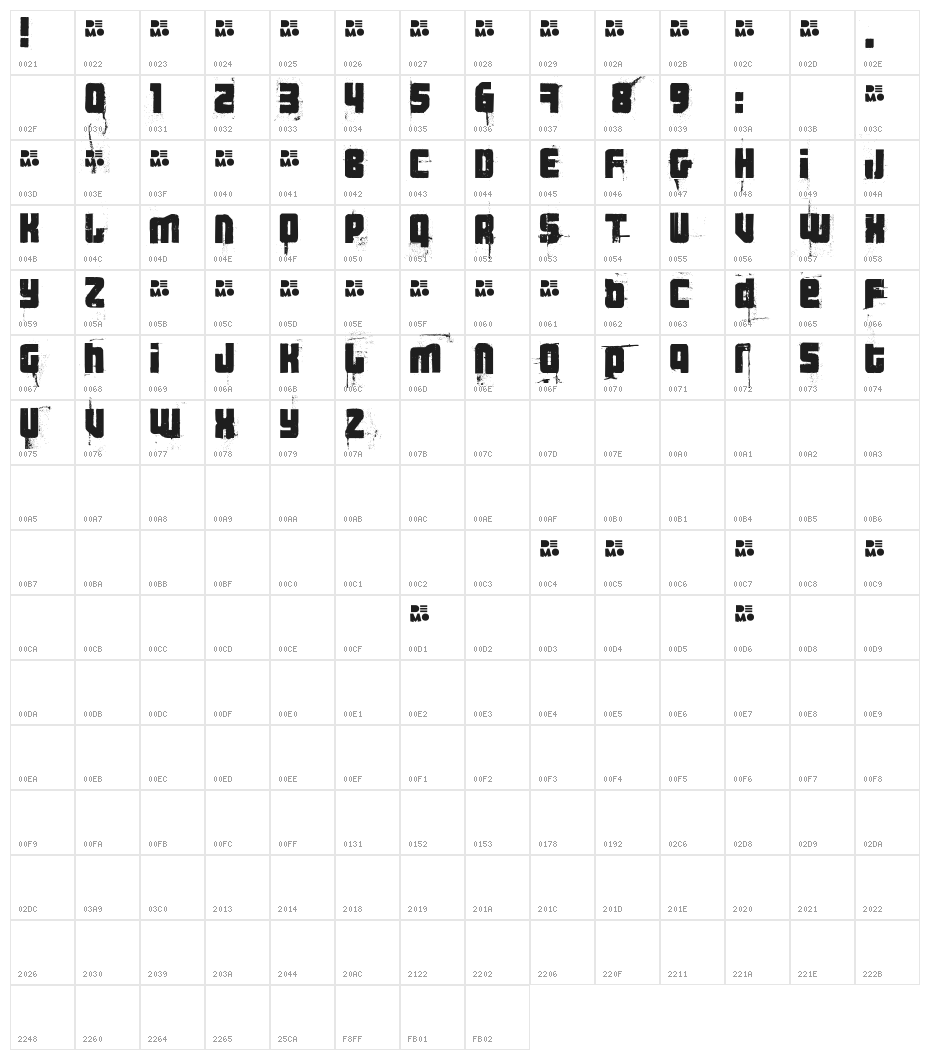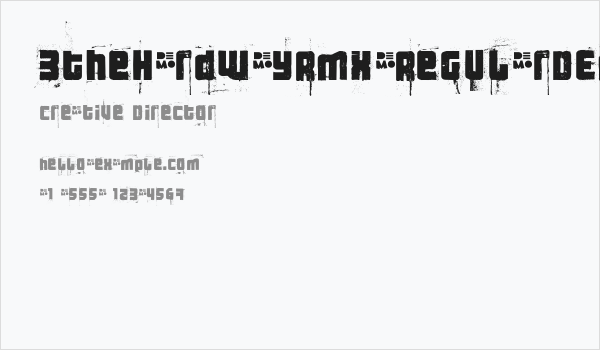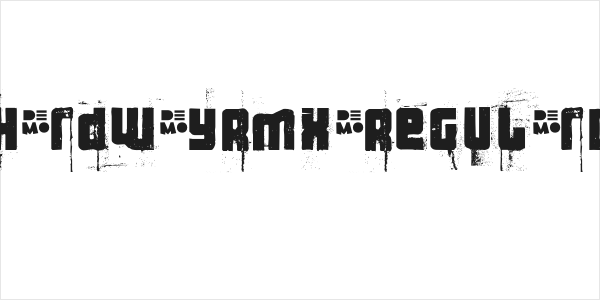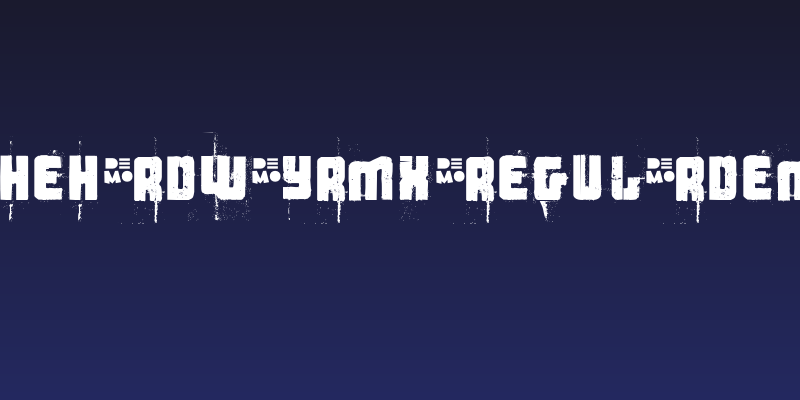
3theHardwayRMX-RegularDEMO Font
| 整体风格 | Urban, Industrial, Edgy |
| 推荐项目 | Ideal for posters, album covers, streetwear branding, or any project needing a bold, edgy look. |